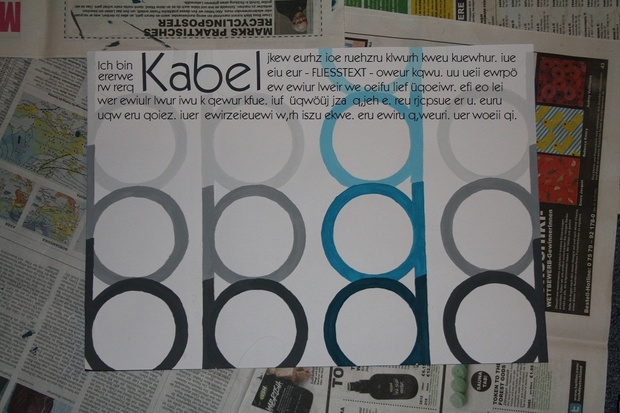
frage zu plakatgestaltung
als kleine hintergrundinformation bevor ich frage:
ich bin 18 jahre alt und schülerin eines gymnasiums mit dem schwerpunkt auf gestaltung und medientechnik.
als projekt müssen wir momentan ein plakat von hand entwerfen und gestalten das kein spezifisches thema hat sondern deren inhalt allein die schrift selbst sein soll. als gestalterische mittel dürfen nur die verschiedenen zeichen und schnitte der jeweiligen schrift verwendet werden.
so und nun zur sache:
mein plakat ist soweit fertig - ich hatte die schrift 'kabel'.
jetzt bin ich mich bei meinem letzten schritt allerdings doch unsicher: neben dem namen der schrift soll auch ein kleiner fliesstext mit infos zur schrift mit drauf sein. und bei der formatierung von eben jenem text bin ich mir unsicher.
ich möchte ihn oben horizontal über das plakat laufen lassen und den namen 'kabel' der verwendet werden muss auch gleich in den text einbauen. dadurch würde der rest des textes bei jedem zeilenumbruch allerdings zwangsläufig wieder an diesem vergrösserten 'kabel' vorbeikommen und den leser vielleicht stören.
deshalb meine frage - ist das schlimm? ist das vielleicht sogar ein no-go und ich sollte es unterlassen? oder ist es doch halb so wild und ich kann diese idee umsetzen?
ich würde mich sehr über einpaar eindrücke freuen. anbei naürlich ein photo damit sie selbst einen blick darauf werfen können.
[ falls sich jemand wundert: mir ist bewusst dass der text sehr ungenau / gequetscht platziert ist. das dient auch nur als grobe vorlage damit man die idee dahinter sieht. bei der umsetzung würde ich mir definitiv mehr mühe geben. :) ]
Ein paar Dinge fallen mir auf:
- Sind dir die Versalien abhanden gekommen? Und das auch noch in deinem Post? :peng:
- Du schreibst "Kabel", zeigst aber die "ITC Kabel", die sich wesentlich von der Kabel unterscheidet. Infos dazu.
- Versalien gehören gesperrt, das hätte dem Wort FLIESSTEXT gut getan.
Um deine Frage zu beantworten: Ich empfinde das als künstlerische Freiheit und auf einem derart gestalteten Plakat hat es seine Daseinsberechtigung. :-)
Und ja jetzt wo du es sagst - ich habe vergessen zu erwähnen, dass unser Lehrer mir die Freiheit gelassen hat mich für eine der Beiden zu entscheiden. Da hab ich lieber die ITC Kabel genommen.
Was genau meinst du mit gesperrt...? Ich entschuldige mich für mein Unwissen aber wie gesagt ich bin noch Schüler und ich beschäftige mich dieses Jahr das erste Mal in meinem Leben mit Typographie deshalb sind einige Dinge mir noch nicht so geläufig.
Eine Frage noch: Was genau meinst du mit 'derart gestaltet' ? Den Aufbau des Plakats oder die Amateurhafte Umsetzung?
Falls letzteres - wäre das also auf einem professionellem Werk nicht gestattet?
Und ja jetzt wo du es sagst - ich habe vergessen zu erwähnen, dass unser Lehrer mir die Freiheit gelassen hat mich für eine der Beiden zu entscheiden. Da hab ich lieber die ITC Kabel genommen.
Das ist ja auch ok, nur würde ich es dann auch hinschreiben. :-)
Was genau meinst du mit gesperrt...? Ich entschuldige mich für mein Unwissen aber wie gesagt ich bin noch Schüler und ich beschäftige mich dieses Jahr das erste Mal in meinem Leben mit Typographie deshalb sind einige Dinge mir noch nicht so geläufig.
Für Unwissenheit muss sich keiner entschuldigen, erst recht dann nicht, wenn sich auf den Weg macht, sein Wissen zu mehren. :gimmifive: Mit Sperren das Erhöhen der Laufweite gemeint, der übertriebene Extremfall sähe so aus: F L I E S S T E X T. Eine moderate Erhöhung (auch Spationieren gemannt) dient der Erhöhung der Lesbarkeit.
Eine Frage noch: Was genau meinst du mit 'derart gestaltet' ? Den Aufbau des Plakats oder die Amateurhafte Umsetzung? Falls letzteres - wäre das also auf einem professionellem Werk nicht gestattet?
Mit "derart" meine ich völlig wertfrei einfach die Art der Gestaltung. Es gibt auf deinem Plakat keinen Mengentext, der durch eine solche Anordnung gestört würde, insofern ist das einfach ein Stilmittel. Solange die Absicht dahinter halbwegs erkannt werden kann, spricht ja nix dagegen.
Ach, noch eines: Die Wörter, die hier in der Textfarbe und unterstrichen sind, führen zum entsprechenden Wiki-Eintrag. Draufklicken lohnt sich :-)
Ich glaube, bertel meinte ganz wertfrei, dass das auf einem Plakat, das auf diese Weise gestalterisch konzipiert wurde, so gestaltet werden kann, wie Du es getan hast. :-)
»Gesperrt« bedeutet, dass Du, wenn Du Text in Versalien setzt, zwischen die Buchstaben mehr Platz geben musst, als das bei gemischter Schreibweise (also Groß- und Kleinbuchstaben) der Fall wäre. Andernfalls stimmt der Schriftrhythmus nicht (der vom Gestalter der Schrift auf die gemischte Schreibweise abgestimmt wurde), die Versalien wirken dann zu dicht gedrängt und die Folge ist ein uneinheitliches, »fleckiges« Schriftbild.